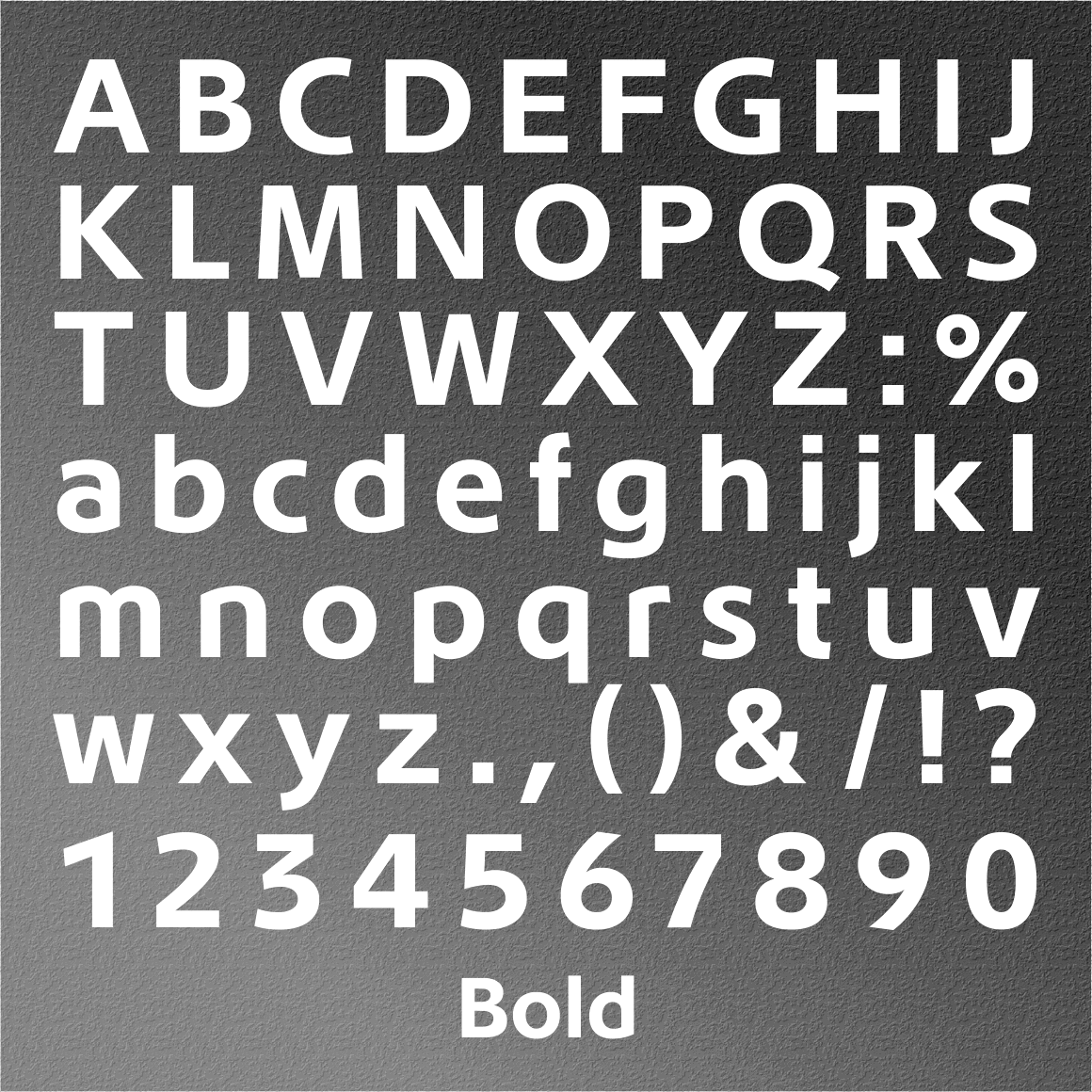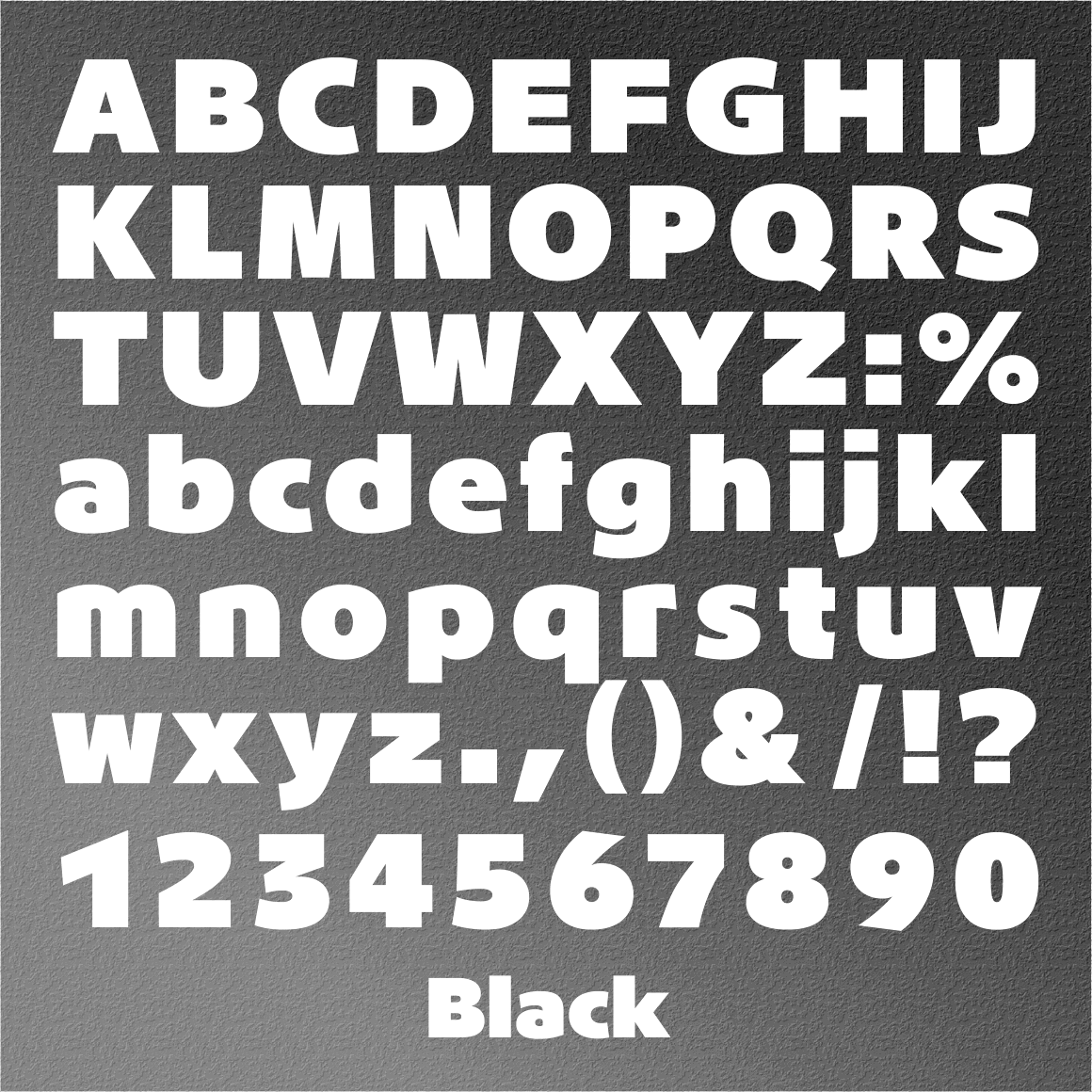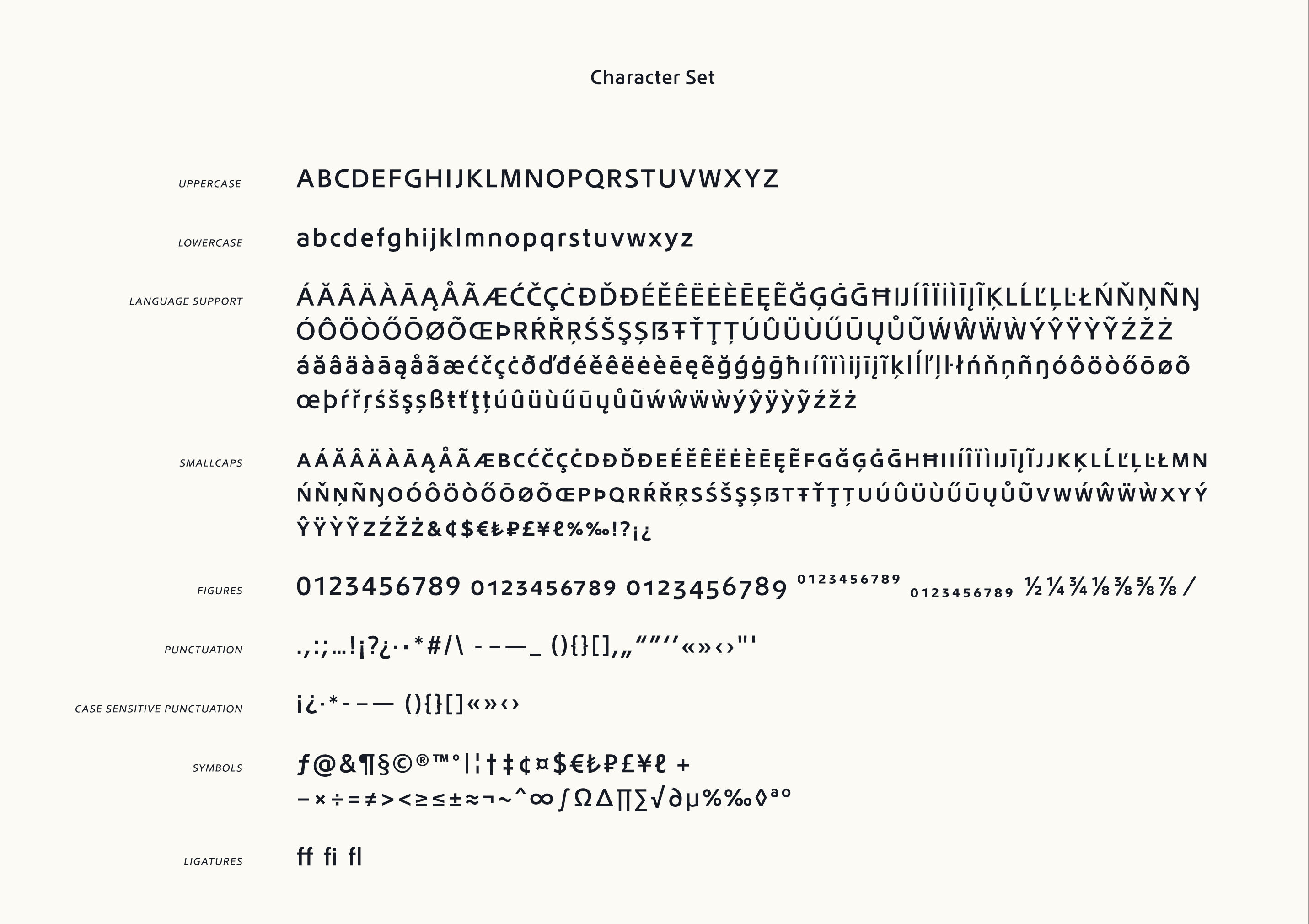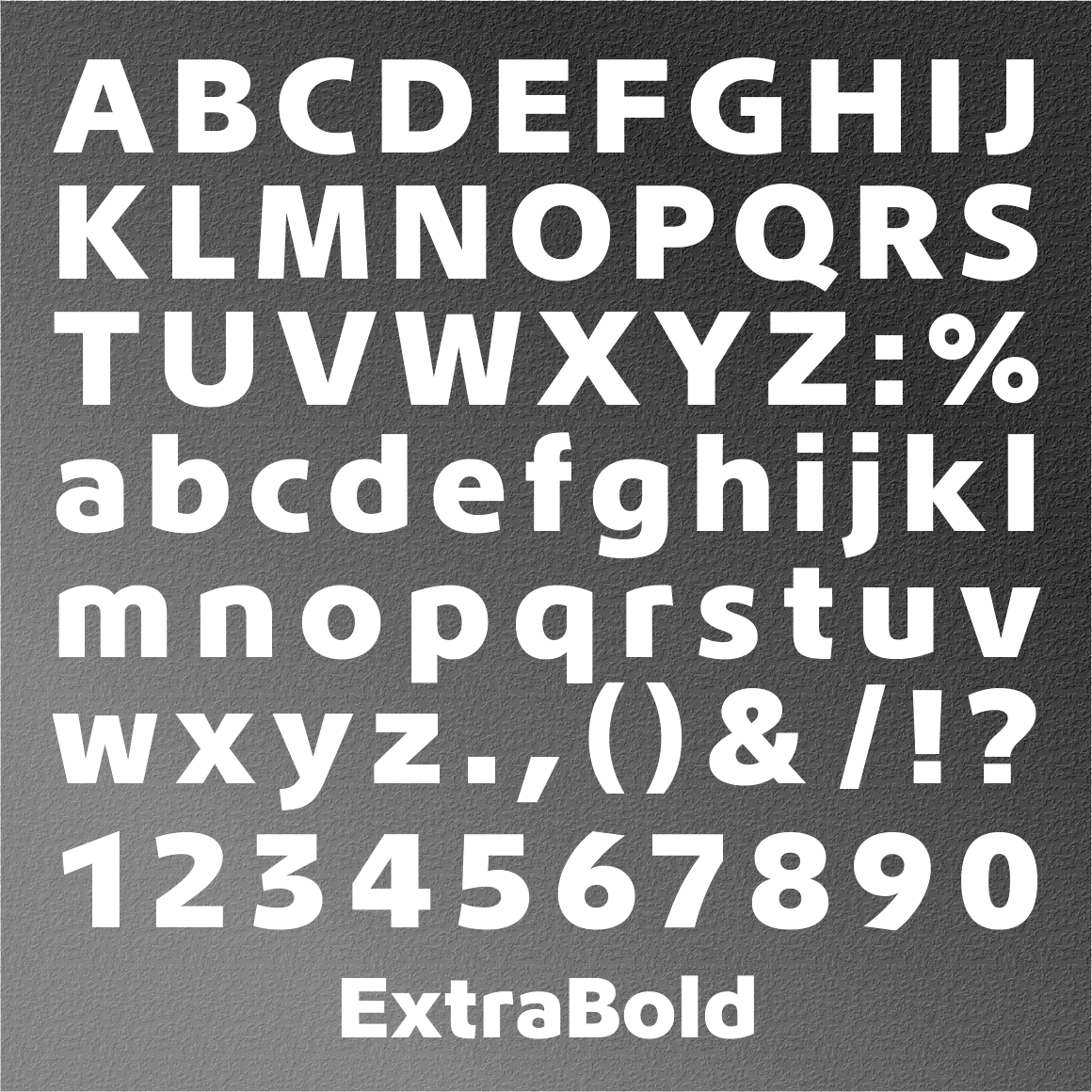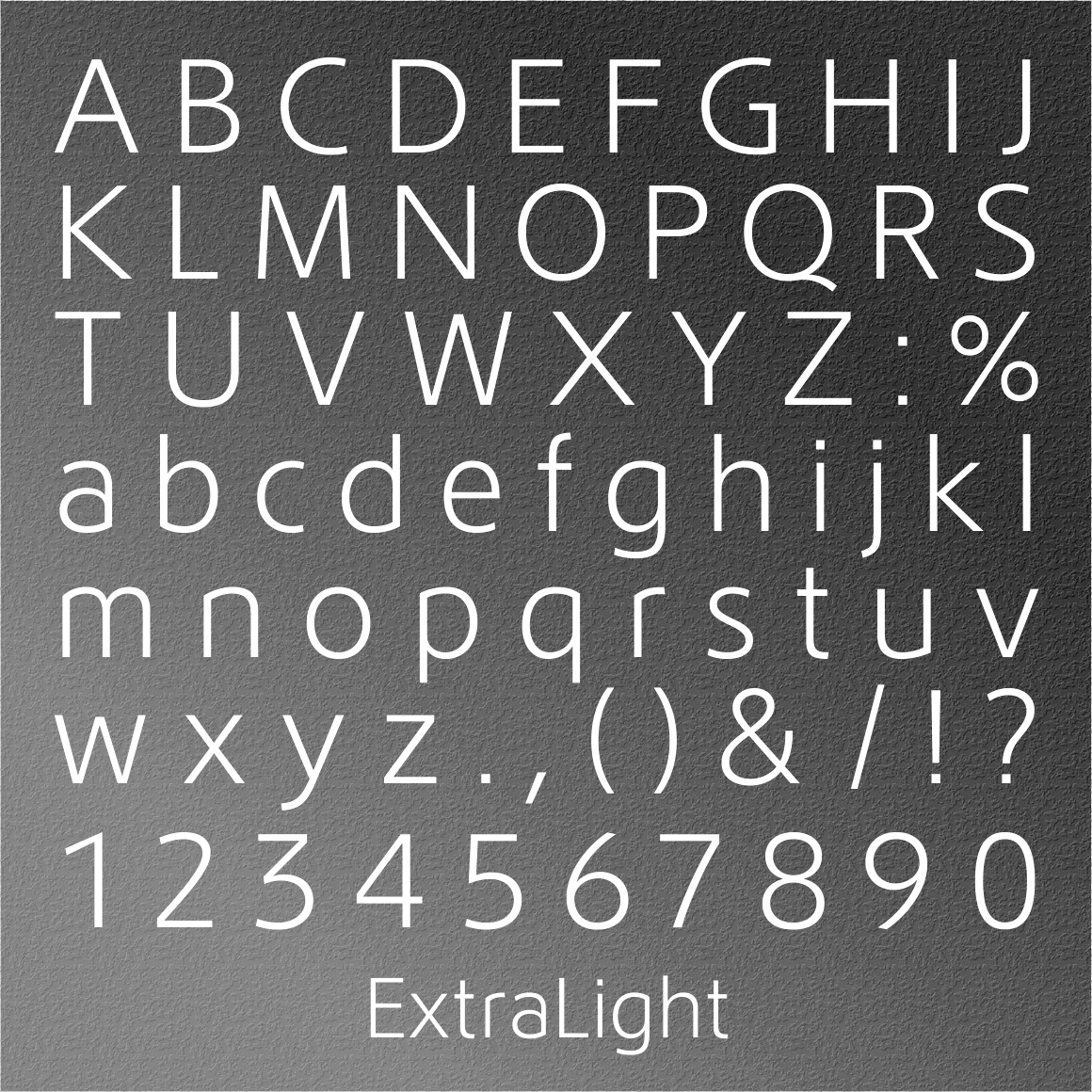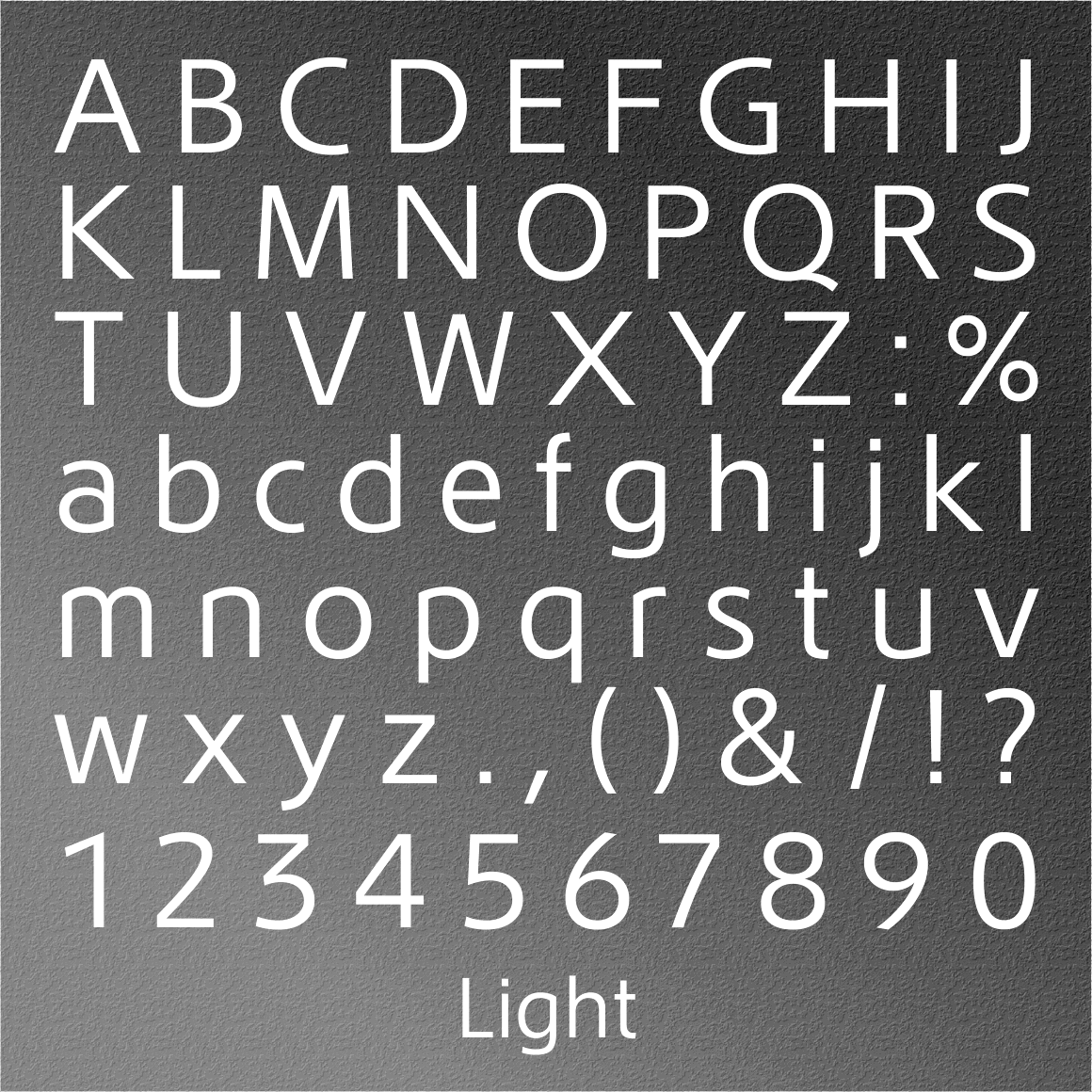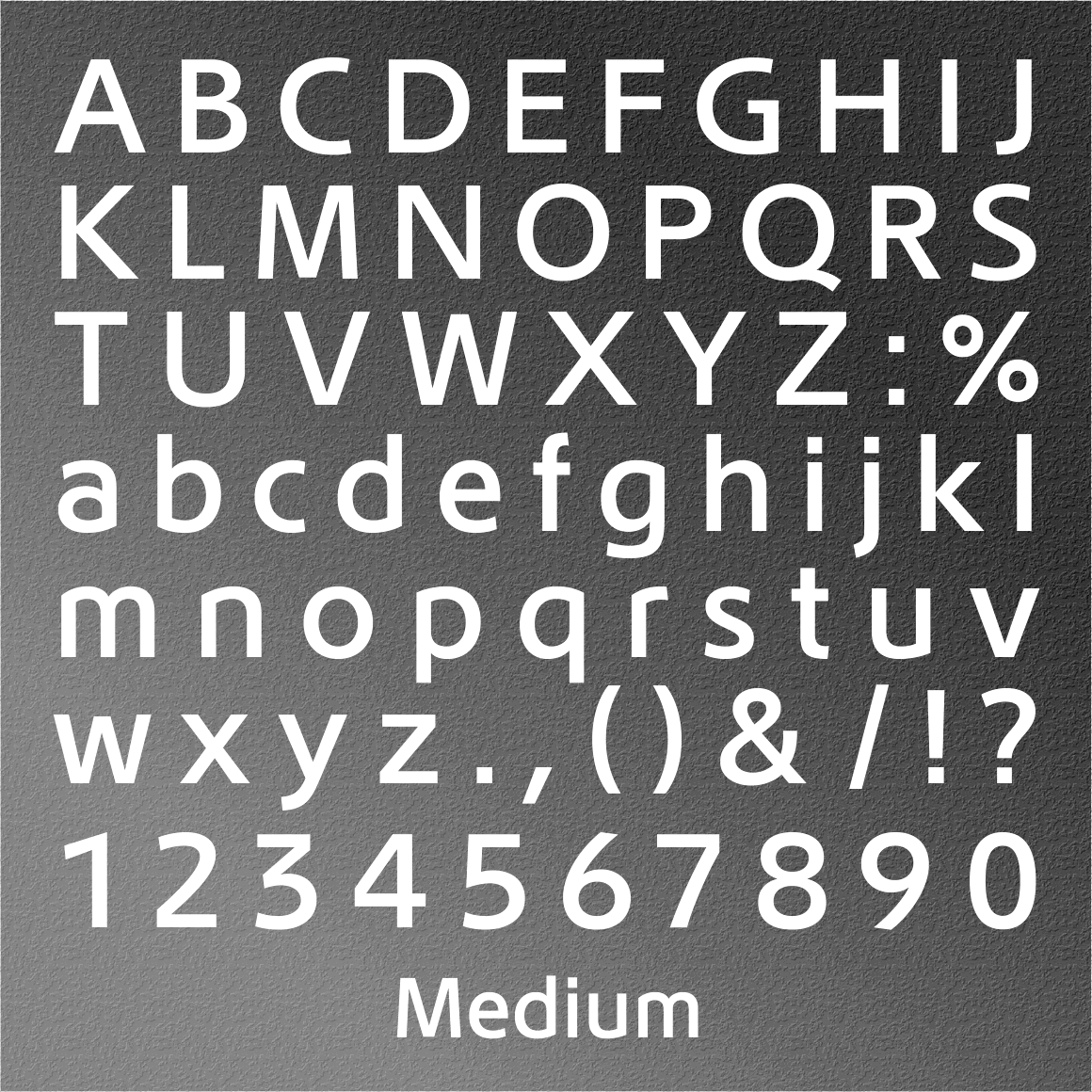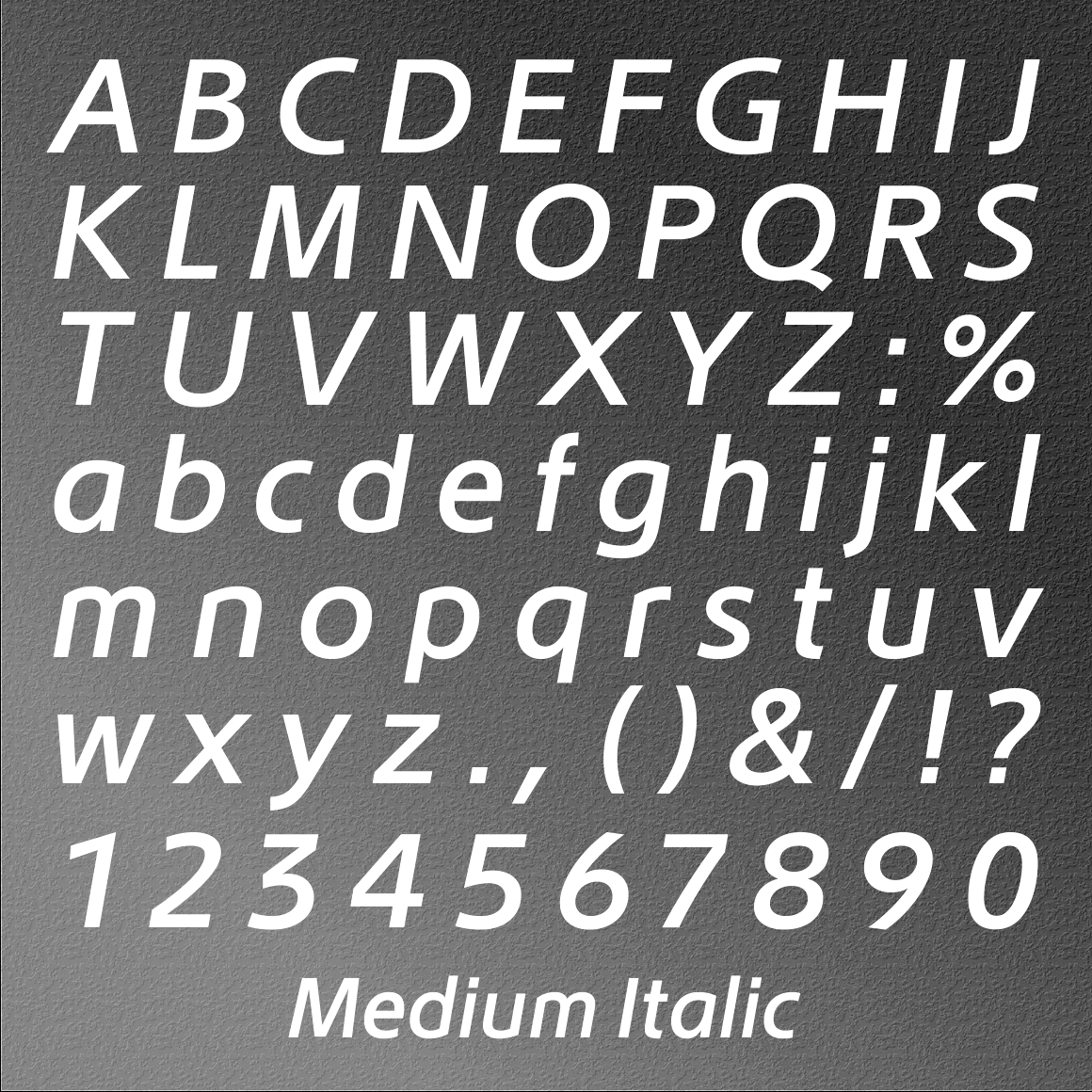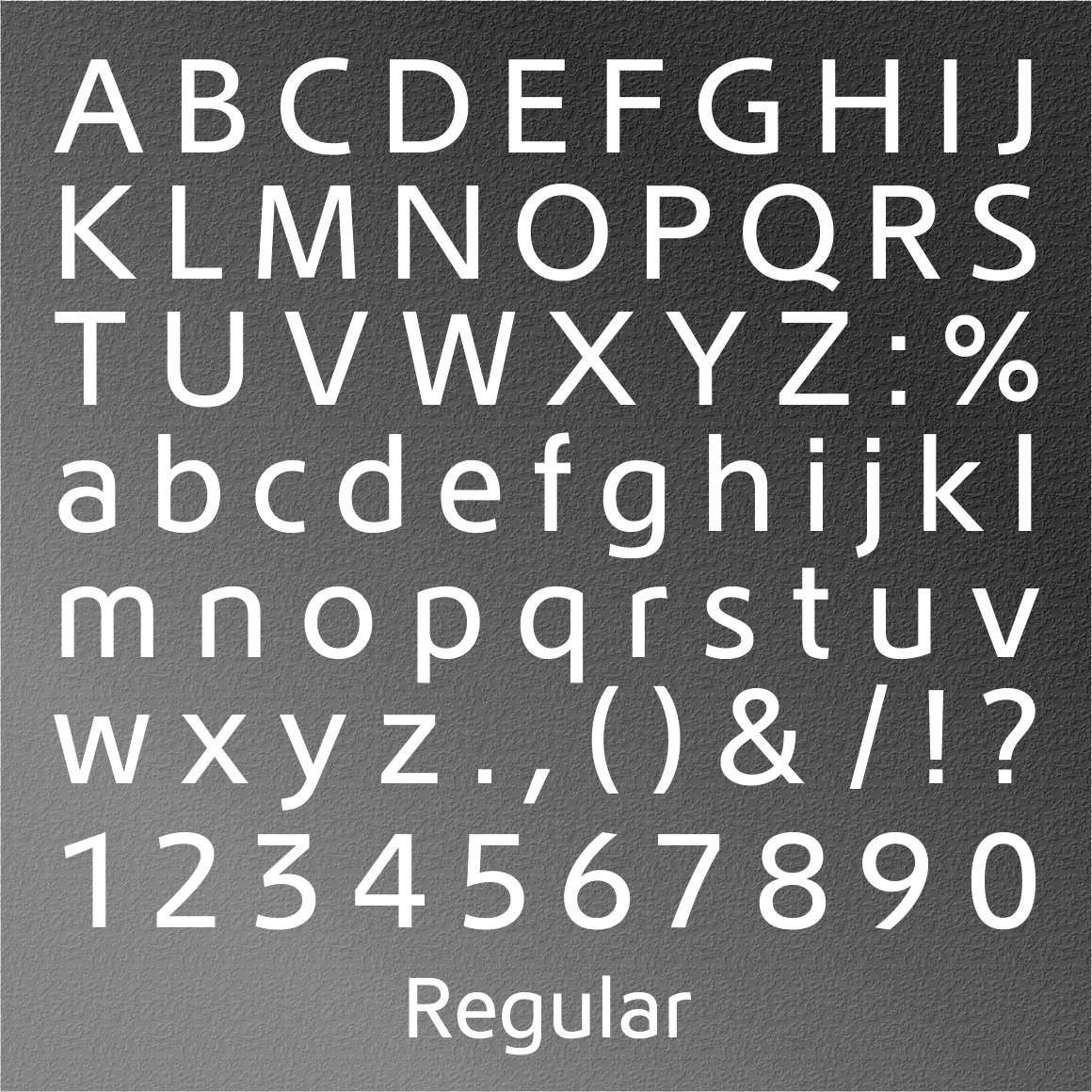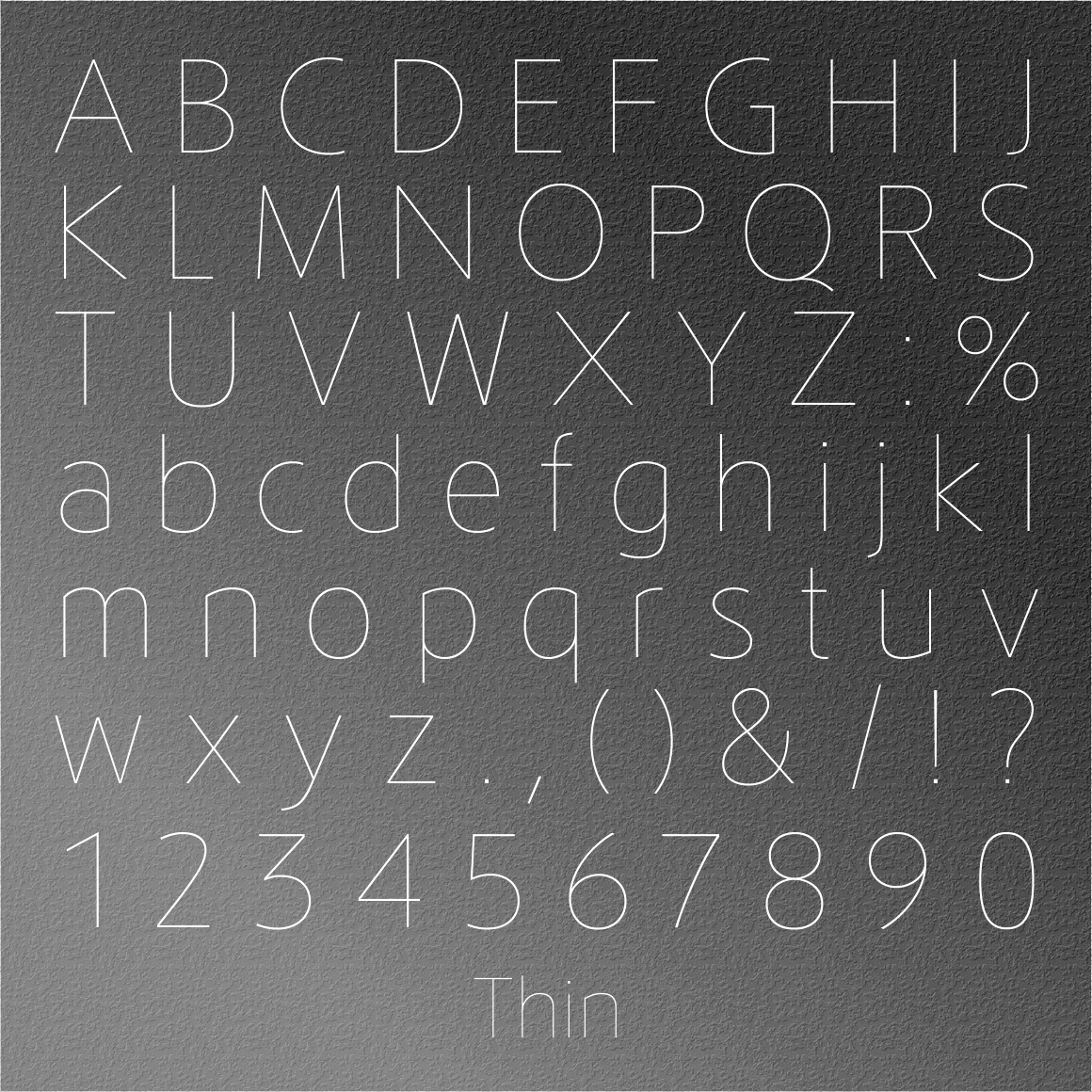
Lotus Eden Sample Medium(無料お試し版)
Lotus Eden Sample Medium Italic(無料お試し版)
Lotus Eden Thin・UltraLight・ExtraLight・Light・Regular・Medium・Bold・ExtraBold・UltraBold・Black・Variable(商品版)
Lotus Eden Thin Italic・UltraLight Italic・ExtraLight Italic・Regular Italic・Medium Italic・Bold Italic・ExtraBold Italic・UltraBold Italic・Black Italic・Variable Italic(商品版)
デザイン
1987年に、第2回モリサワ賞 国際タイプフェイスコンテスト欧文部門で2位となった「Lotus medium」 が、外部デザイナーの協力によって10ウェイトの「Lotus Eden」として完成した。
フォントデザイン:佐賀野 宇宙
連想されるイメージ
・優しさ・丸み・カーブがキレイ・柔らかい・ゆったり・美しい・リズム・モダン・新鮮・ちょっとクラシカル・ヒューマニストサンセリフ…
・グリフ数 657(Mac OS Roman、Windows-1252、Adobe Latin 3をカバー)
・ヨーロッパ主要32言語以上に対応
・OpenTypeフィーチャーにより、スモールキャップ、オールドスタイル数字、大文字用字形、分数表示、化学用上付き下付き数字などに対応。